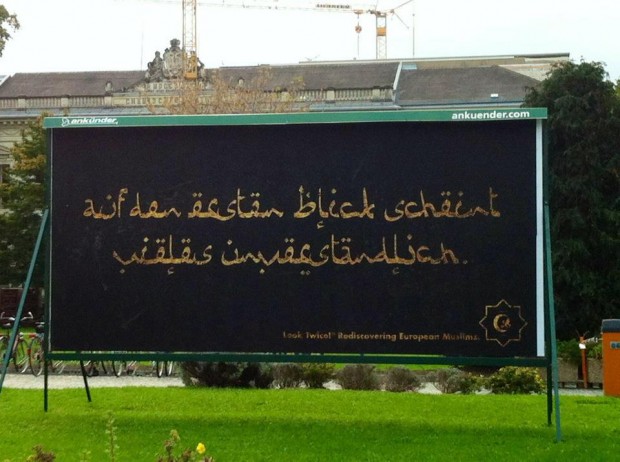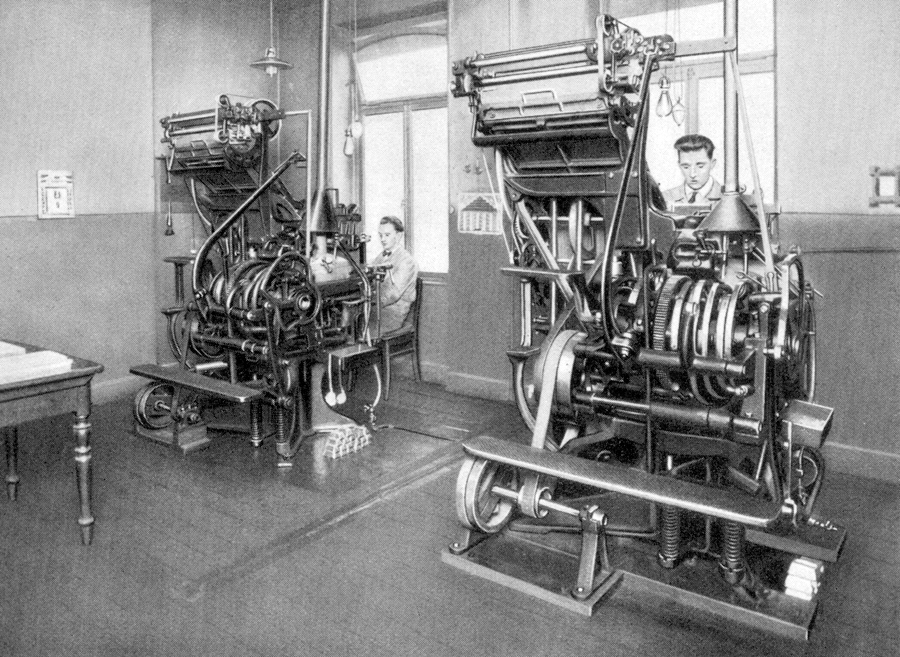
Schöne Frisuren haben die beide :-P
Von wann ist das ungefähr?
Ich würde ja auch frühe Dreißiger tippen, das ist aber geraten. Gibt es noch irgendwelche Rechte an den Bildern?
Von der Fotoqualität würde ich auch nach dem ersten Weltkrieg und von den Frisuren her vor dem zweiten Weltkrieg schätzen :-P
Fotoqualität
Sind das Fotos? :shock: Ich dachte, dass sind Bleistiftzeichnungen … :schonklar:
Wir vermuten, dass es irgendein Mischmasch aus Photos bzw. von Hand übertragenen Photos und technischen Zeichnungen ist – zusammen mit irgendeiner alten Drucktechnik.
Dann war der Besuch beim Augenarzt neulich ja doch nicht für die Katz’ :-)
Von meinem neuen Augenarzt halte ich nicht allzu viel, vielleicht zu Recht :shock:
Und die Politik erst ...
(Plakat zum Frauenstimmrecht in der Schweiz – ich glaube das hatten wir hier irgenwann schon mal, es passt aber grade dazu)
Armer schwarzer Kater ...
Der kriegt bestimmt Schelte, wenn die Frau vom Wählen zurück kommt ...
Dieses Plakat muss dem Tierschutzverein gemeldet werden!
Die TAZ erfreut die Leser mit einer neuen Serie über Bibliotheken im Norden, die ich trotz der drohenden lex Springer, vulgo auch Leistungsschutzrecht genannt, verlinke:
Teaser-Text:
„Lesen und lesen lassen“, die neue Serie der taz.nord, beschreibt Bibliothekszustände in Norddeutschland. Büchereien demokratisieren das Wissen – aber gibt ihnen die Wissensgesellschaft dafür auch die notwendigen Mittel? Strengen sie sich selbst genug an, um aktuelle Kommunikationsräume zu bleiben? Oder ist nicht sowieso schon alles im Netz?! Eine Antwort-Suche vor Ort in acht Stationen.
Sollte jemand eine in meinen Augen komplett sinnbefreite rT-Ligatur benötigen: Bittesehr …
Auf eine verschrobene Art aber doch irgendwie gut gelöst eigentlich …
Nur das die Lesbarkeit für vorbeifahrende Fahrzeuge auf der Strecke bleibt :-?
... aber eigentlich erkennt man ja, worum es geht :-P
Wo ich schon am Schreiben bin: Weihnachten wird auch immer morbider!
Meint der Vorschlag eigentlich …láche oder …làche?
Forget about the End of the World …
Wobei einstweilen offenbleiben muß, was das kleinere und was das größere Übel wäre.